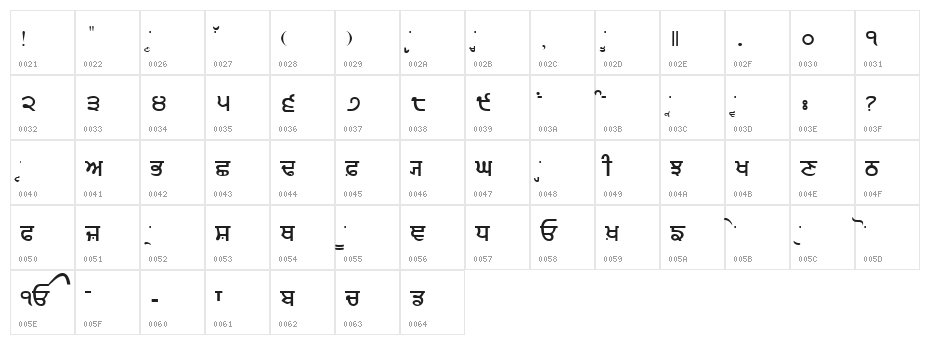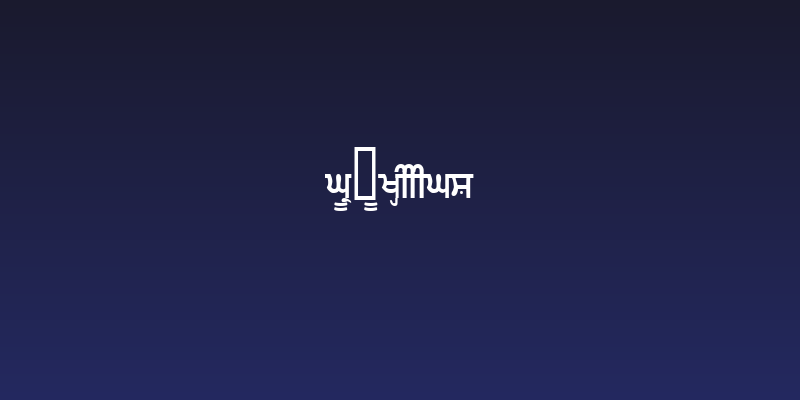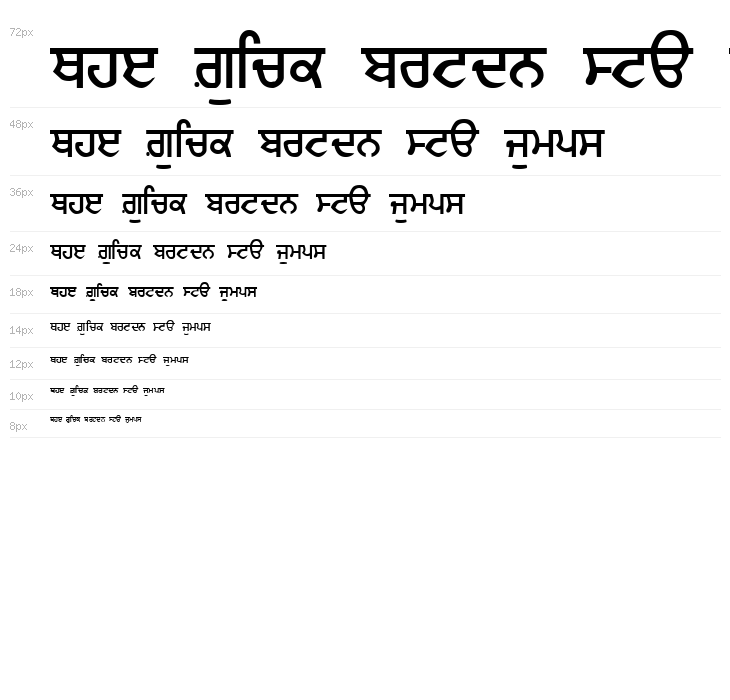
GurmukhiIIGS Font
| Estilo general | Classic |
| Caso de uso | Headlines, Body text, Educational materials |
| Proyectos propuestos | This font is perfect for educational materials, cultural publications, signage, and any project requiring clear and impactful Punjabi text. |